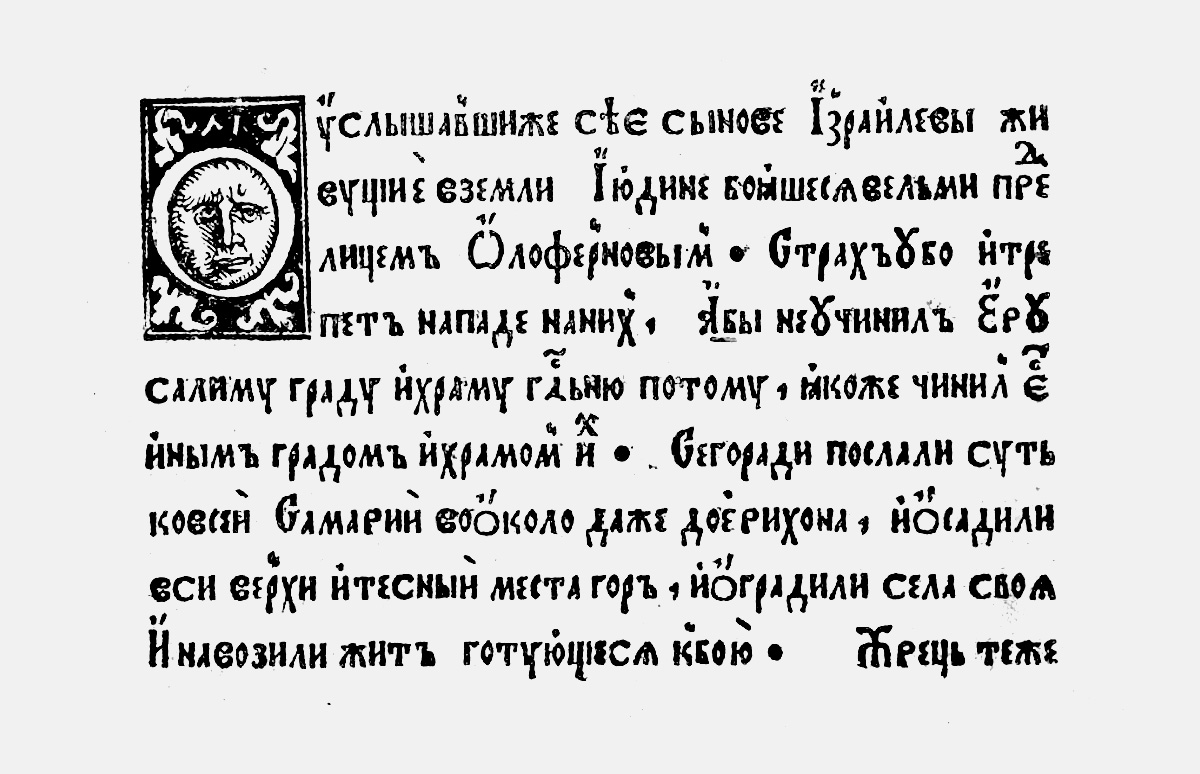
Кириллица
в русской культуре
Участники конференции ATypI в Санкт-Петербурге в 2008 году могли слышать одноимённый доклад Юрия Яковлевича Герчука. Один из ключевых моментов выступления — попытка автора чётко обозначить место реформированного шрифта в русской культуре, ведь, вслед за импортированным стилем европейской архитектуры, техники, одеяния, гражданский шрифт был неотъемлемым звеном культурной революции Петра I. Великий самодержец не мог не осознавать, что новый шрифт (изначально задуманный как универсальный инструмент) посягал на сложившуюся многовековую традицию оформления богослужебных книг, и в итоге ограничил сферу применения гражданского шрифта светскими изданиями. Не менее интересен малоизученный и сегодня вопрос происхождения форм букв реформированного шрифта. Редакция журнала добавила к докладу ряд иллюстраций и предлагает получившийся исторический очерк вашему вниманию.
ётр I писал своему торговому агенту, голландскому купцу Христофору Бранту, о заказываемых через него в Амстердаме новых литерах: «И как сию азбуку получишь, и слова (буквы, литеры. — Ю. Г.) будут готовы, всех трёх рук (размеров, кеглей. — Ю. Г.) напечатать „Отче наш“ или иное что краткое и прислать на почте». Письмо было написано 29 января 1707 года, в период активной работы над проектированием и изготовлением нового русского шрифта. 8 ноября 1708 года он же писал князю М. П. Гагарину о новых московских литерах и просил «напечатать какую-нибудь и молитву тою азбукою, хотя „Отче наш“, и прислать с тою азбукою». И опять через три дня — И. А. Мусину-Пушкину о поправках в азбуке, которую также просил прислать ему «с какою-нибудь молитвою, напечатанною оными литерами».
Образец набора гражданским шрифтом. Азбука гражданская с нравоучениями. 1710. Мировая цифровая библиотека.
Речь идёт во всех случаях о пробах шрифта, который назовут впоследствии «гражданским». Сам Пётр предназначит его в январе 1710 года для печатания книг «исторических и манифактурных», то есть светских, в противоположность церковным, для которых был сохранён прежний полуустав. Почему же царь просил напечатать этими литерами именно молитву?
Ну, положим, что было обычным печатать в качестве образца нечто благочестивое. Но всё равно его пожелание определённо противоречило принятому назначению новых литер. Очевидно, в планах Петра произошли за короткое время важные изменения. Шрифт, задуманный сперва как универсальный, получил более узкое назначение. Документальных данных об этом нет, но легко понять вероятную причину такого решения. Новшество, коренным образом меняющее облик религиозной книги, грозило чрезвычайными общественными потрясениями. Полустолетием раньше незначительные поправки в её текстах и в церковных обрядах уже вызвали церковный раскол.
Сравнение набора дореформенным и гражданским шрифтом. 1709 г. Этот лист был приложен печатниками Московской синодальной типографии к поданной на имя государя челобитной, в которой «нижайшiе раби гражданскiе типографiи наборщики» (как они сами себя назвали) просили поднять расценки на набор гражданским шрифтом, так как он, по их мнению, был «убористее» славянского. Источник: Азбука съ исправленіями Императора Петра Великаго и Указомъ Его о введеніи въ употребленіе гражданскаго шрифта. СПб.: Типографія В.С. Балашева, 1877.
Богослужебная книга была предметом священным, материализацией Слова Божия. И функционально, и стилистически она была органично включена в систему церковных обрядов. Её зримый образ и, в частности, форма текста защищались многовековой традицией. Кириллица пришла на Русь вместе с православием, в составе богослужебной и религиозно-учительной книги, как её главная часть: само Слово. Её дальнейшая эволюция была замедленной. Новые формы письма также приходили к нам от единоверцев: полуустав, вязь, а с ними и новые типы книжных орнаментов, появлялись в Болгарии по крайней мере полустолетием раньше, чем на Руси. Можно думать, что это не признак «отставания» или недостатка творческого начала, но результат особой бережности к традиционному образу писанного слова.
Кириллица — славянское письмо, принятое в православных странах, — объединяла исповедующих эту веру славян в некое культурное сообщество, наглядно — через характерный облик письма — противопоставленное «латинянам» (католикам), а позднее и протестантам.
Возвращаясь к культурному смыслу петровской шрифтовой реформы, следует напомнить, что она была органической частью целостной программы перестройки русской культуры по европейским барочным образцам, и важнейшей частью её был отрыв от средневековых корней, смена традиции, радикальное преобразование стиля. А значит, новый шрифт был создан не потому, что был, как иногда писали, «удобнее» старого, «больше подходил» для технической и научной литературы или даже был «понятнее». Очевидно, что для людей, воспитанных на старой книге, он понятнее не был, напротив, создавал лишние затруднения. Зато он был необходимым звеном культурной революции Петра Первого. Гражданский шрифт стоит в ряду таких явлений петровской культуры, как введение европейского костюма, париков, обязательного для правящего сословия бритья бород и т. п. (однако представителей духовенства такие новшества не коснулись). Царь изменил летоисчисление, насаждал европейские формы архитектуры (в том числе даже церковной) и живописи, вводил светские праздники с фейерверками и триумфальными арками.
На арках этих уже в 1703 году делались, как гласит старинный источник, «надписи российскими словами, по виду начертания латинского характера». Очевидно, такие начертания казались более соответствующими ордерной архитектуре арок, аллегорическим фигурам, а возможно, и самой идее триумфа. Латинизировались, судя по гравюрам начала XVIII века, надписи на декорациях ранних петровских фейерверков и иллюминаций. Другими ранними опытами европеизации кириллицы были русские тексты на выполнявшихся иностранными гравёрами географических картах.
Новая и достоверная всея Европы карта. Гравёр Алексей Зубов. Москва. Оружейная палата, Мастерская П. Пикарта. 1720–1721, 1760–1770. 1-й из 6 листов. РНБ.
Но всё это были лишь частные проявления нового духа времени. Введение же нового наборного шрифта стало государственной акцией, которая целенаправленно придавала русским печатным изданиям европейский облик. Ведь кроме самого шрифта переворот этот решительным образом преобразил, приблизив к западным образцам, также и печатную светскую книгу в целом. Страница её стала светлой и лёгкой, печать на ней стала мельче. Структура и весь облик русских изданий, печатавшихся гражданским шрифтом, сразу же подчинились европейским нормам своего времени. Новшества коснулись титульного листа, спусковых и концевых полос, характера и техники воспроизведения иллюстраций, барочной символики, справочного аппарата и т. п.
Разворот из книги Эрнеста Брауна «Новейшее основание и практика артиллерии». Гравюры П. Пикарта и Г. Девита. Москва. Печатный двор, 1709 г. РГБ.